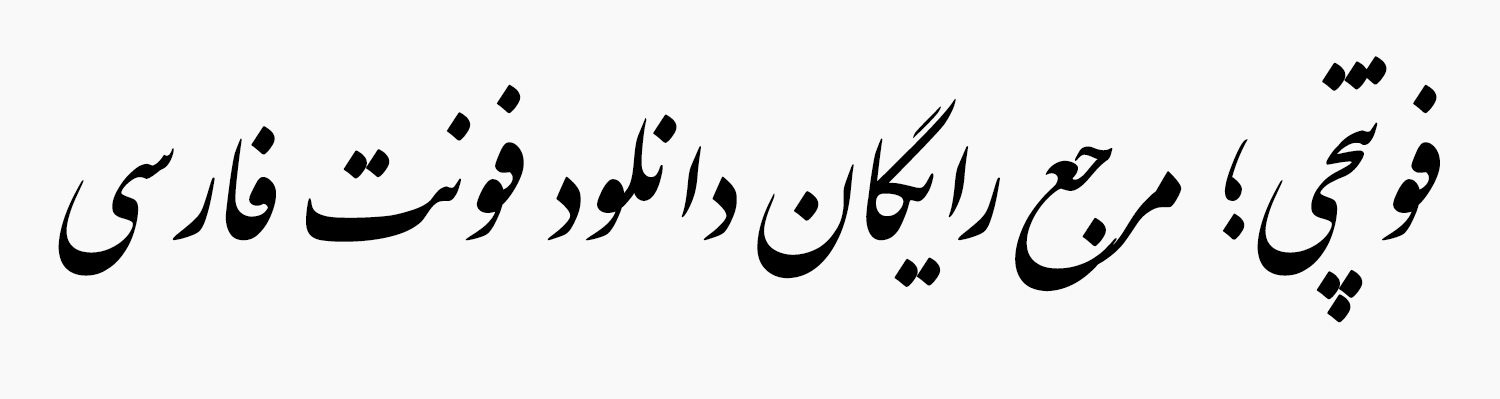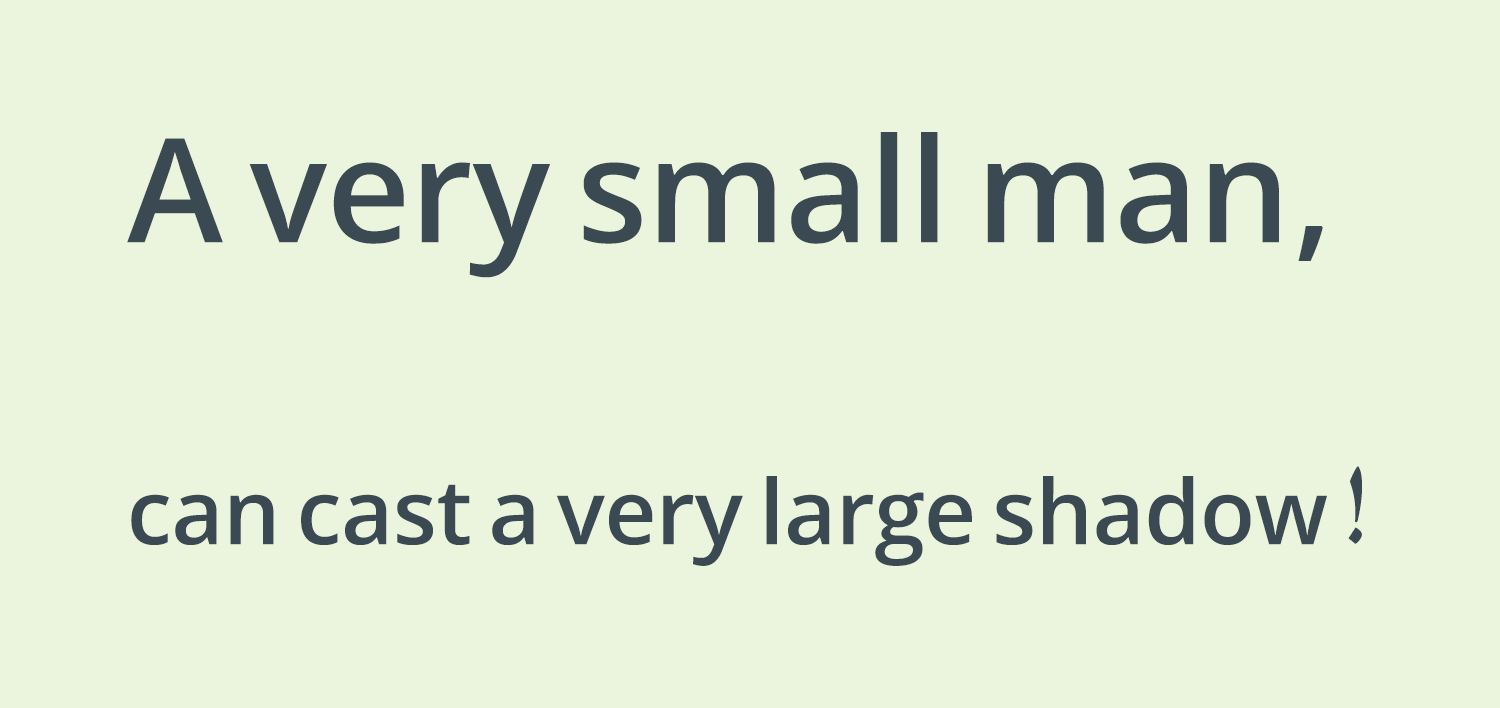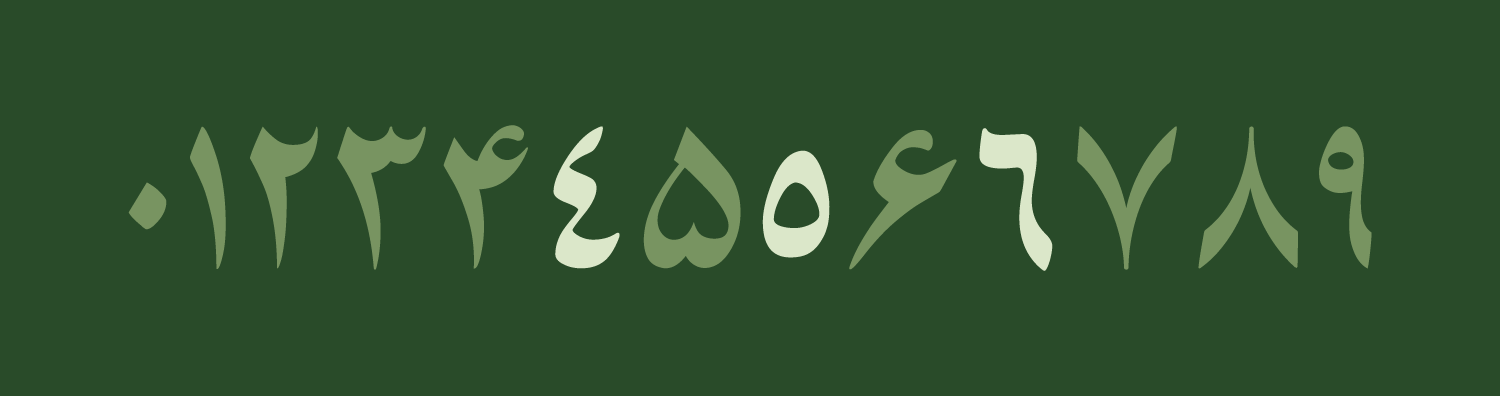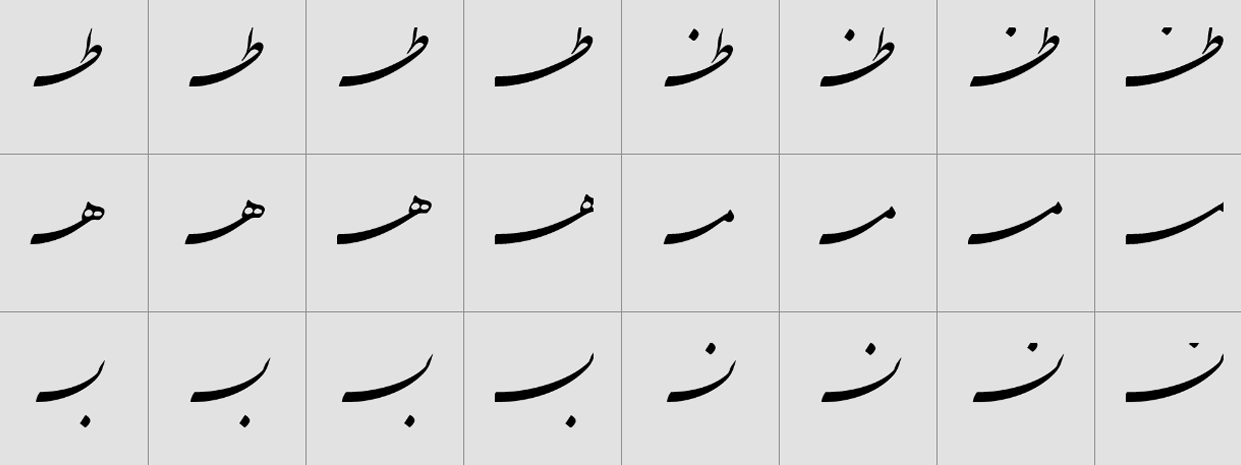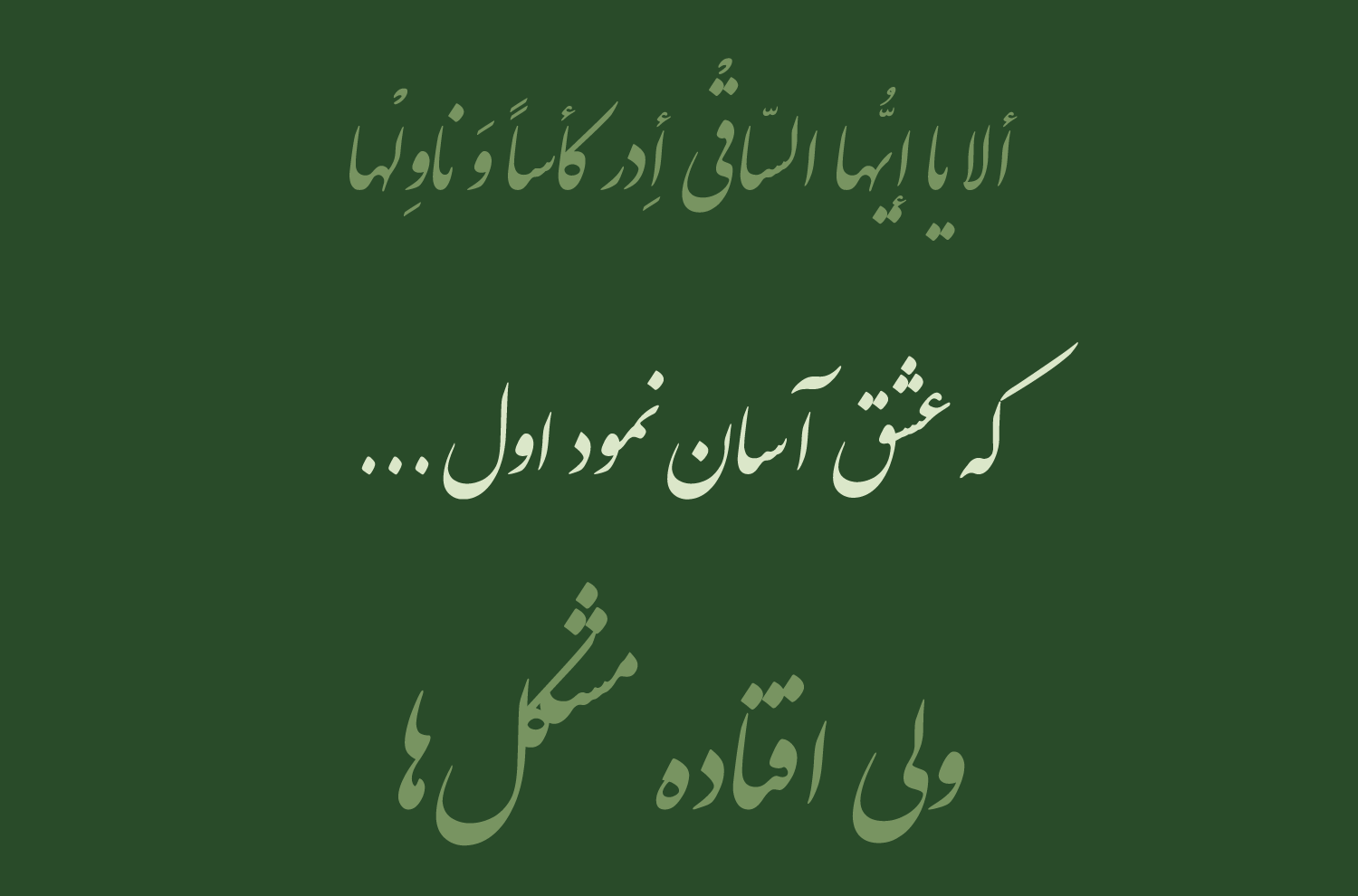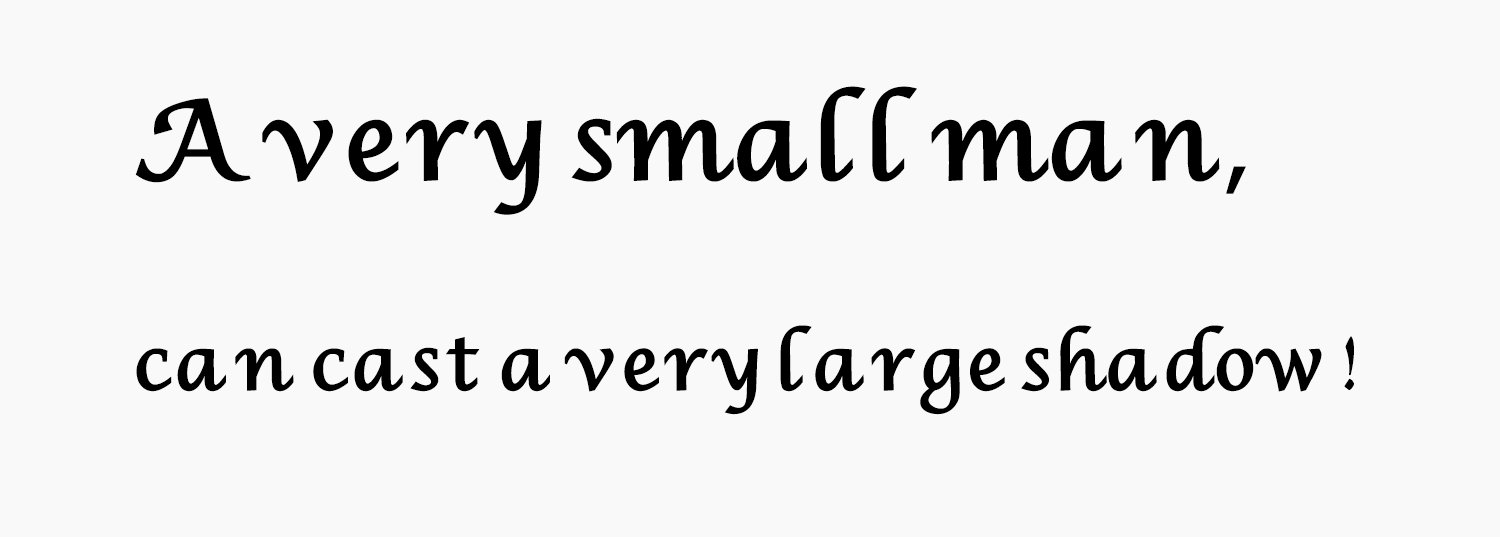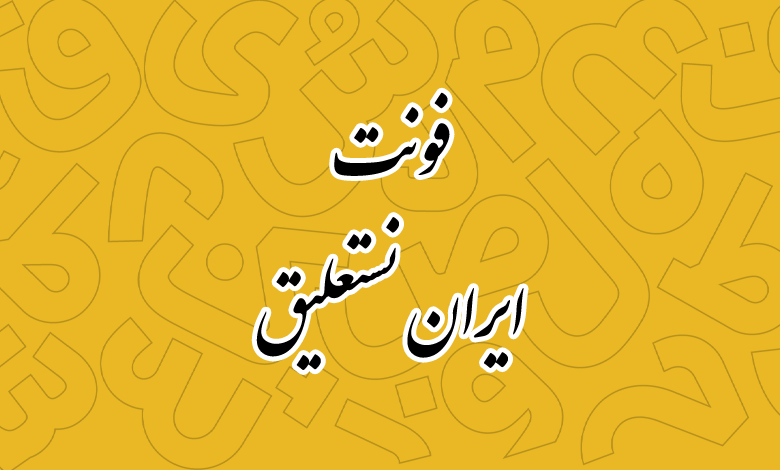
فونت ایران نستعلیق ۳.۰۹ (IranNastaliq)
فونت نستعلیق یا ایران نستعلیق (به انگلیسی: IranNastaliq) نسخه دیجیتالی از خطاطی خوشنویسی ایرانی است که چند سالی از عرضه آن میگذرد. سالها پیش نسخه اولیه ایران نستعلیق رایگان عرضه شد. در زمانی که دسترسی به خط نستعلیق در محیطهای نرمافزاری همچون فتوشاپ و ورد وجود نداشت، ارائه این نسخه با حمایت شورای عالی انقلابی محسوب میشد.
این فونت توسط حسین زاهدی طراحی شده است. با وجود استقبال گستردهای که از این فونت شد، اما با وجود ایرادات فنی مختلف، این فونت نمایانگر روح خطاطی ایرانی نبود. مشکلاتی که در این نسخه وجود دارد عبارتند از:
- عدم رعایت کرسیبندی: در نسخه رایگان، بسیاری از کلمات روی خط کرسی نمینشینند و تعادل بصری متن به هم میریزد.
- تداخل حروف: گاهی انتهای یک حرف با ابتدای حرف بعدی برخورد میکند یا فاصلهها (Kerning) آنقدر غیرمنطقی است که خوانایی را دشوار میکند.
- گلیفهای ناقص: بسیاری از ترکیبات جایگزین و حروف کشیده در نسخه رایگان وجود ندارد. این یعنی شما مجبورید با همان شکل پیشفرض و گاها غلط کلمات را تایپ کنید یا اینکه دست به دامان نرمافزارهای گرافیکی سنگین شوید.
استفاده از نسخه رایگان برای یک طراح گرافیک حرفهای، مثل این است که یک نقاش ماهر، با قلمموی شکسته نقاشی کند؛ نتیجه هرچقدر هم خوب باشد، ابزار کار نقص خود را نشان میدهد.
فونت ایران نستعلیق ۳: یک بازطراحی کامل
وقتی از نسخه ۳ صحبت میکنیم، منظورمان تغییرات جزئی یا ساختار وزنی نیست. صحبت از بیش از ۲۰۰۰ اصلاحیه فنی و هنری است.
در فونت نستعلیق ۳ طراحان با استفاده از سرمایه شخصی تصمیم به بازطراحی کامل این فونت کردند. دیگر خبری از حمایت شورای عالی و این دست موارد نبود. به همین دلیل این نسخه در قالب یک نسخه پرمیوم و کاملا اختصاصی عرضه شده است که به جهت حمایت طراحان و سازندگان فونت باید از مرجع رسمی ایران نستعلیق، آن را خریداری کنید.
از جمله تغییرات و دلایلی که باید از نستعلیق ۳ استفاده کنید:
- رفع ۲۰۰۰ باگ و ایراد ساختاری: تکتک گزارشهایی که در طول سالها درباره خرابی حروف، نقاط جابجا شده و اتصالات غلط داده شده بود، در این نسخه بررسی و رفع شدهاند.
- ساختار خوشنویسی صحیح: در خوشنویسی نستعلیق، هر کلمه شخصیت خودش را دارد. نسخه رایگان در بسیاری از ترکیبات، این اصول را نقض میکرد. اما نسخه ۳ با وسواس بسیار زیاد و زیر نظر اساتید، بازنگری شده تا وقتی متنی را تایپ میکنید، انگار واقعا با قلم و مرکب نوشته شده است.
- گلیفهای جایگزین و کشیدگیهای استاندارد: تنوع ترکیبات و فرمهای حروف به شما اجازه میدهد تا خلاقانهتر تایپ کنید و نگران دفرمه شدن کلمات در حالت کشیده نباشید.
فونت نستعلیق از زبان فارسی و عربی پشتیبانی میکند. بر خلاف نسخه رایگان ساختار انگلیسی فونت تغییر کرده و با فونت دیگری جایگزین شده است. در ادامه تصاویری از این فونت را مشاهده میکنید که با نسخه ۲ نیز مقایسه شدهاند.
فونت نستعلیق با توجه به اینکه یک فونت نمایشی و تزئینی است از اعراب پشتیبانی کاملی دارد. در زبان عربی یا حتی فارسی زمانی که از اعراب همراه با کاراکترهای «سکون، تشدید یا همزه» استفاده کنید، همنشینی مناسبی با هم دارند تا کلمات بههم نریزد.
یکی از عمده مشکلات فونتهای خوشنویسی قدیمی همین مسئله است که برای رفع این مشکل فونت نستعلیق دارای گلیفهای ترکیبی است تا در ترکیباتی که این بههم ریختگی رخ میدهد، همنشینی و چینش کاراکترها به شکل اختصاصی اعمال گردد تا بدون نیاز به طراحی نرمافزاری بهسادگی بتوانید با ساختار استاندارد این قلم حروف را تایپ کنید.
دارای ترکیبات و حروف جایگزین متعدد
فونتهای خوشنویسی دارای ساختاری نمایشی هستند که با حروف و ترکیبات جایگزین قابل پیادهسازی است. از سوی دیگر برای حل مشکل فاصله گذاری و چینش حروف، اجبارا برخی حروف شاید دارای بیش از ۱۰ گلیف مختلف باشند.
مانند نمونه در تصویر زیر میبینید که حروف و ترکیبات «ط، ظ، م، ه، ن، ب» با توجه به اینکه با چه حروفی همراه شده و چه کلمهای را تشکیل دهند، دستکم در ۴ حالت مختلف قابل تایپ هستند.
با استفاده از ترکیبات جایگزین در تنظیمات Open Type نرمافزارهای گرافیکی نظیر فتوشاپ، میتوانید حروف و ترکیبات متعددی را به شکل و شیوه دلخواه خود تایپ کنید.
این فونت حروف را در چند سبک متعدد که شامل ساختار فشرده، کشیده، چندگانه و گاهی ترکیبی هستند در دسترس قرار داده است که بر اساس استانداردهای حروف نستعلیق میتوانید از آنها استفاده کنید.
پشتیبانی از اعداد فارسی و عربی استاندارد
ویژگی دیگر فونت نستعلیق پشتیبانی استاندارد از اعداد فارسی و عربی است که در این قلم بر اساس استاندارد بینالمللی بوده و گلیف خاص خود را دارند.
اعداد «۴۵۶» عربی که دارای سبک متفاوتی نسبت به اعداد «۴۵۶» فارسی هستند طراحی شده است. البته شاید فکر کنید که عدد صفر فارسی چرا به صورت تو خالی نیست؛ دلیل این امر این است که در خط نستعلیق عدد صفر به همان شکل عربی با نقطه استفاده میشده است.
مناسب کارهای فرهنگی و هنری
بهترین کاربردی که فونت نستعلیق دارد برای کارهای فرهنگی و هنری است که میتواند شامل طیف وسیعی از نیازها از طراحی کارهای گرافیکی گرفته تا طراحی محصول در حوزه دکوراسیون باشد.
بسته به اینکه شما در چه حوزهای فعالیت دارد میتوانید از فونت نستعلیق استفاده دلخواهی داشته و با تواناییهای گرافیکی خود آثاری فاخر را تولید کنید.